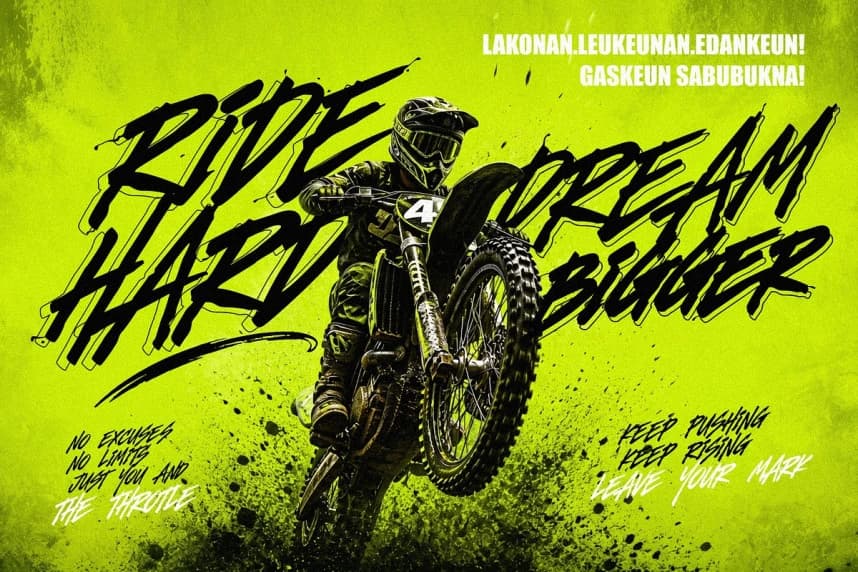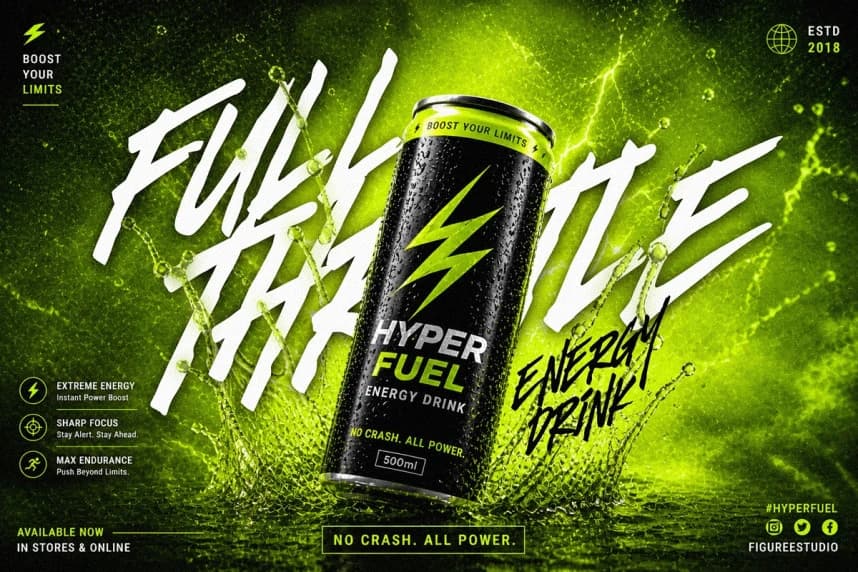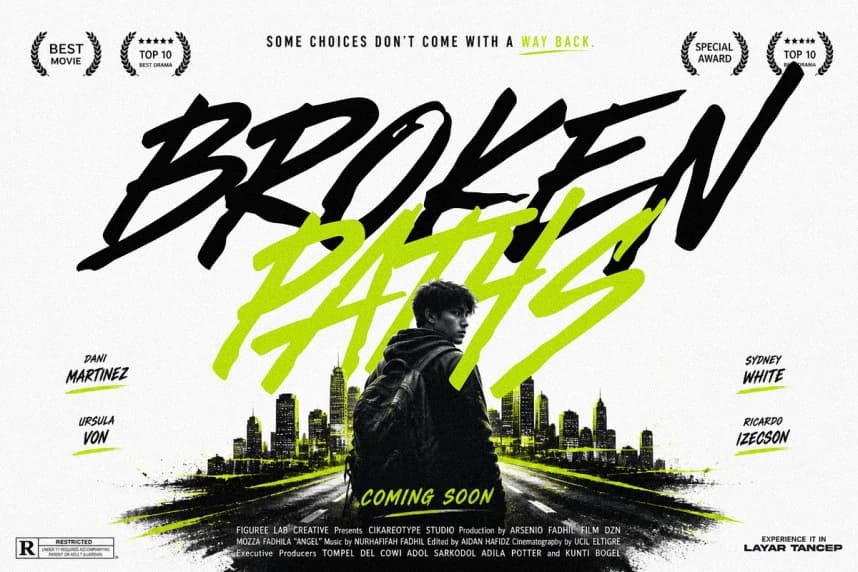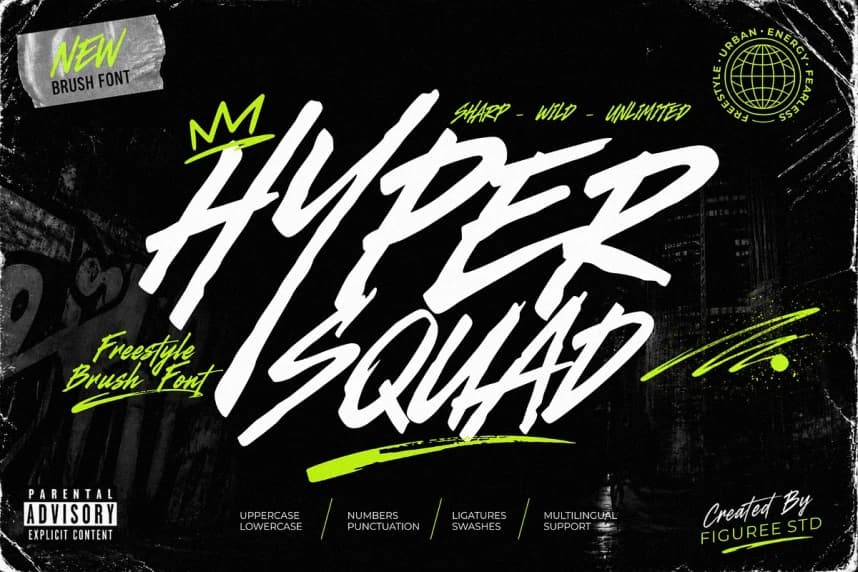
Hyper Squad Font – Freestyle Brush Font, yazı tipinize doğal hareket ve ifadeli enerji kazandırmak için tasarlanmıştır. El boyaması darbelerinden ilham alan bu yazı tipi, spontan ve karakter dolu bir organik fırça stili sunar.
Hyper Squad Font – Freestyle Brush Font, tipografinize doğal bir hareket ve ifade gücü kazandırmak için tasarlanmıştır. El boyaması darbelerden ilham alan bu yazı tipi, organik bir fırça stili sunar ve kendiliğinden oluşan bir karakter hissi verir.